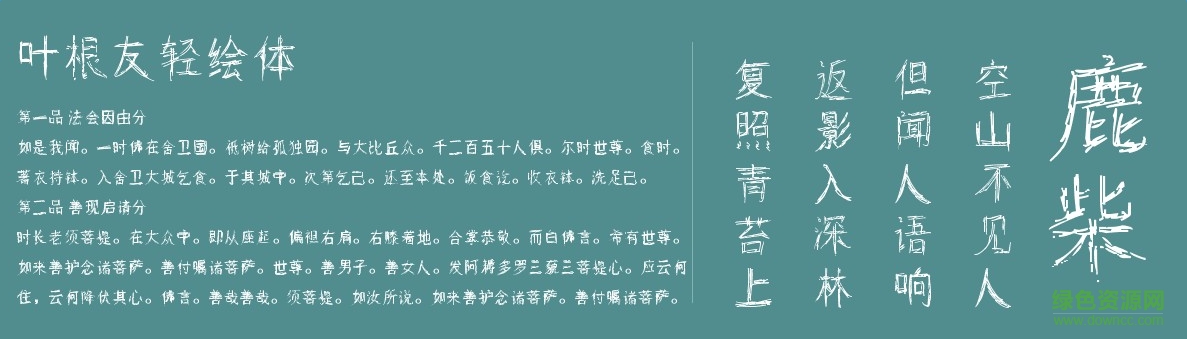
葉根友輕繪體是一款由知名書法家葉根友創(chuàng)造的字體,比劃圓潤(rùn),適用于廣告、藝術(shù)設(shè)計(jì),海報(bào)設(shè)計(jì)等方面,有需要的朋友們不要錯(cuò)過(guò)了。歡迎大家來(lái)綠色資源網(wǎng)踴躍下載哦!
葉根友輕繪體,一款輕松自在的字體,所有筆畫均由碎片線條組成,狂野的追逐著中國(guó)漢字手寫的那點(diǎn)放縱。
該字體非常有趣,感覺(jué)字體非常輕,如同漫步一般,又如同在黑板上寫字。